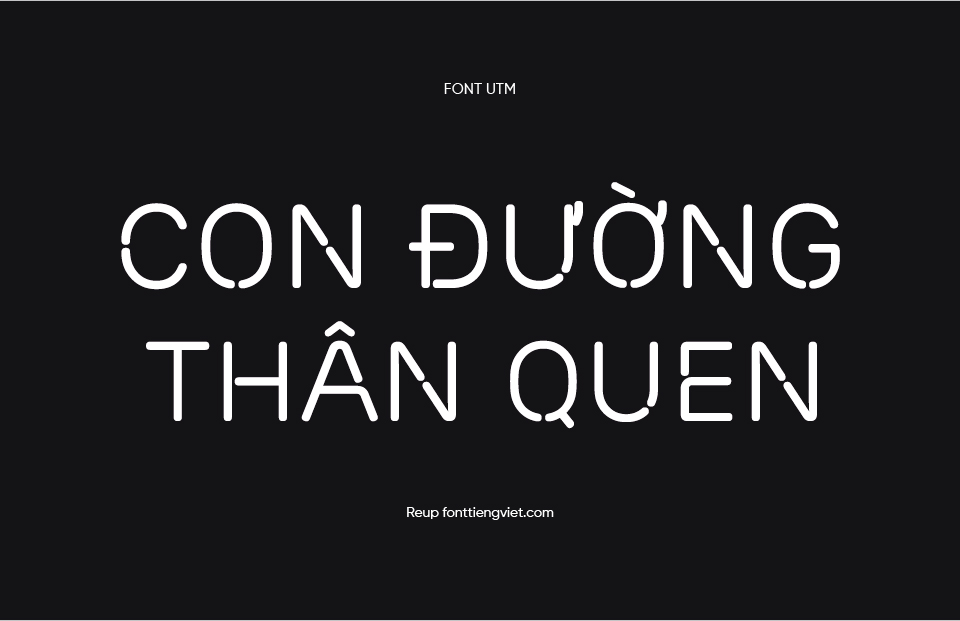
Font Việt hóa UTM Ericsson Capital
Giới thiệu về Font Việt hóa UTM Ericsson Capital
Trong thế giới đồ họa hiện đại, việc lựa chọn một bộ Font Miễn Phí chất lượng đóng vai trò quan trọng trong việc truyền tải thông điệp. Font Việt hóa UTM Ericsson Capital là một trong những kiểu chữ mang phong cách mạnh mẽ, hiện đại và vô cùng chuyên nghiệp. Được tinh chỉnh để phù hợp hoàn toàn với bảng mã tiếng Việt, bộ font này giúp các bạn học sinh và giáo viên dễ dàng tạo ra những slide thuyết trình sinh động hoặc các ấn phẩm truyền thông học đường bắt mắt mà không lo lỗi font hay thiếu dấu.
Ưu điểm nổi bật của Font Việt hóa UTM Ericsson Capital
Thiết kế hiện đại và tinh tế
Đặc điểm nhận dạng của Font Việt hóa UTM Ericsson Capital nằm ở những đường nét vuông vức, dứt khoát nhưng vẫn đảm bảo được sự thanh thoát cần thiết. Kiểu chữ này cực kỳ phù hợp cho các tiêu đề lớn, banner sự kiện hoặc bìa sách giáo khoa. Với độ dày nét đồng đều, font chữ này duy trì khả năng đọc tốt ngay cả khi hiển thị trên màn hình máy tính hay in ấn ra giấy, giúp nội dung bài học trở nên rõ ràng và dễ tiếp thu hơn đối với học sinh.
Khả năng ứng dụng đa dạng trong học đường
Không chỉ dùng cho thiết kế chuyên nghiệp, Font Việt hóa UTM Ericsson Capital còn là công cụ đắc lực cho các bài tập nhóm hay dự án sáng tạo. Bạn có thể sử dụng nó để làm nổi bật các ý chính trong sơ đồ tư duy hoặc trang trí báo tường kỹ thuật số. Sự tương thích cao với các phần mềm phổ biến như Word, PowerPoint hay Photoshop giúp người dùng tiết kiệm thời gian chỉnh sửa và tập trung tối đa vào nội dung sáng tạo của mình.